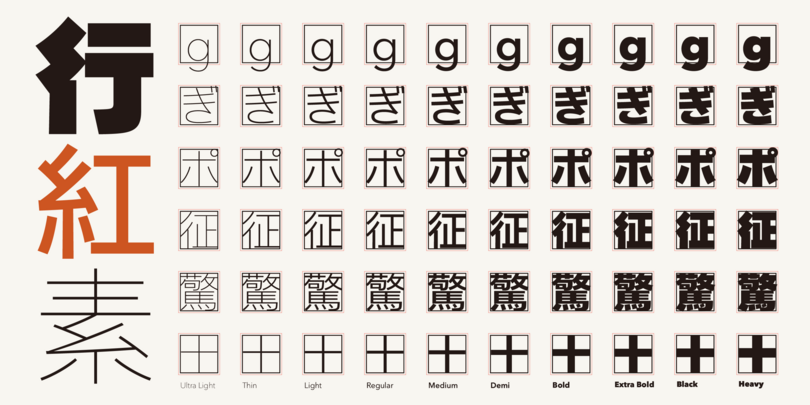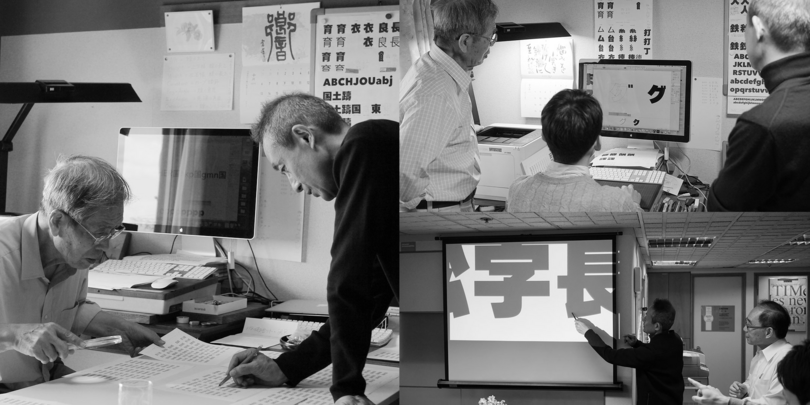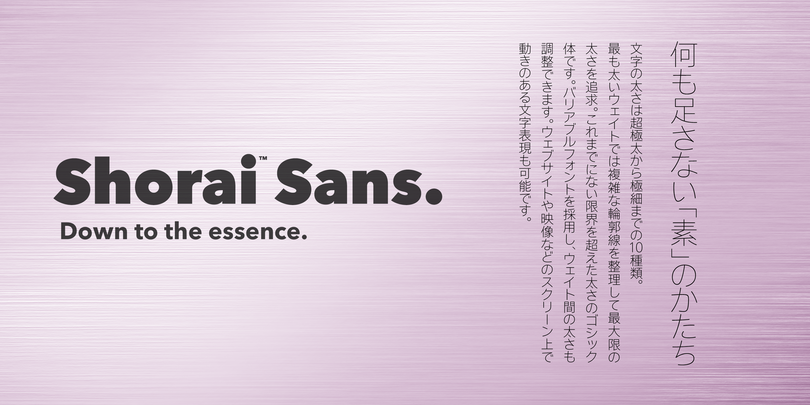
Shorai™️ Sans:何も足さない「素」のかたち
Shorai™️ Sansは、Avenir® Nextの造形的要素を取り入れてデザインされたジオメトリック・サンセリフ体で、たづがね®角ゴシックに続く Monotypeの日本語書体です。Avenir Nextの幾何学的な特徴を活かし、文字の線を均一に保ちました。骨格を極限まで単純化し、すっきりとした形にまとめています。
付属欧文には和文にあわせてサイズや位置を調整した Avenir Nextを採用し、和欧混植に最適化しました。和文と欧文を別々の書体から選ぶ必要がなく、Shorai Sans単体で美しく読みやすいテキストを組むことができます。また、OpenType機能のプロポーショナルメトリクスとカーニングを使用することにより、書体デザイナーが設定した値を反映させた美しいツメ組が可能です。
Shorai Sansは、アドリアン・フルティガー氏と Monotypeクリエイティブタイプディレクターの小林章が制作した Avenir Nextにあわせる新しい日本語書体として、2018年より開発がスタートしました。1970年から 80年代の日本語ゴシック体に大きな変革をもたらした書体デザインの第一人者、中村征宏氏を制作メンバーに迎え、Monotypeの小林章、土井遼太の 3人で文字の形を考えていきました。
Avenir Nextで最も太いHeavyに相当するウェイトから制作を開始。極太で画数が多い文字の場合、それぞれの線の太さや重なり具合のバランスを取るためには常に創意工夫が必要とされます。Shorai Sansでは中村氏を始め小林・土井が試行錯誤を行い、今までにないアプローチでシンプルかつ大胆で絶妙な調整が行われました。例えば、漢字「得」のぎょうにんべんや平仮名「な」では、独特な線の重ね方がされており、書体の個性がよく現れています。
「Shorai Sansは、限界を超えるデザイン、実験的な試みに挑戦したと言えるでしょう。Heavyは一般的なサンセリフ書体よりかなり太くつくっていますし、ひとつひとつの形はギリギリまで簡略化して、文字の内側の空間がすっきり見えるようにしています。これは新しい時代のサンセリフです」(小林章)
基本となる漢字400字ができる頃、Monotypeの日本、香港、ドイツオフィスの書体デザイナーとエンジニア、そして中村氏が香港に集まり、1週間ほど一緒に書体制作をしました。日本語書体の制作では、書体デザインを終えてからエンジニアにバトンタッチするのではなく、両方を同時に進めた方が効率的であると過去の経験から学んだためです。将来の字種拡張も考慮し、最初から多国籍メンバーで開発を進め、世代や文化を超えたコラボレーションとなりました。
「中村さんの発想はいつも斬新で、驚きとわくわくの連続でした。世代を超えたコラボレーションによってできあがったこの書体からは、幾何学的だけれども、どこかに人の手の動きが伝わってくるのです。人のいる未来を描いているのがShorai Sansです」(土井遼太)
「Shorai Sansは、英文字感覚の平仮名ですね。私のように日本の字だけをつくってきた人にこの線は出せない。この書体が完成後に社会でどのように使われるのかを見たいと思います」(中村征宏氏)
Avenir Nextにあわせ、Shorai Sansも超極太から極細までの10ウェイト(Ultra Light、Thin、Light、Regular、Medium、Demi、Bold、Extra Bold、Black、Heavy)での展開となりました。最も太いHeavyでは、複雑な輪郭線を整理し、最大限の太さを追求。これまでにない限界を超えた太さのゴシック体になりました。バリアブルフォントを採用し、ウェイト間の太さの調整も可能です。文字数はAdobe-Japan1-3(OpenType StdN)に準拠。デスクトップ用のほか、ウェブ、ePub、HTML5を使用したデジタル広告などのライセンスを選択できます。
たづがね角ゴシックは、Neue Frutiger®にあわせたヒューマニスト・サンセリフですが、Shorai SansはAvenir Nextにあわせたジオメトリック・サンセリフに分類されます。求められる用途や雰囲気にあわせて、2種類のサンセリフを使い分けることにより、表現の幅がさらに広がります。
書体名の「Shorai(ショウライ)」は、松の枝を吹き抜ける風や音の意味である「松籟」に由来しています。茶道では茶釜の湯がたぎる音を意味し、日本的で優雅な響きのある名前です。誰でも発音しやすく、世界中の方々にお使いいただける日本語書体です。
和欧混植に最適化され、Shorai Sans単体で美しく読みやすいテキストを組むことができます。